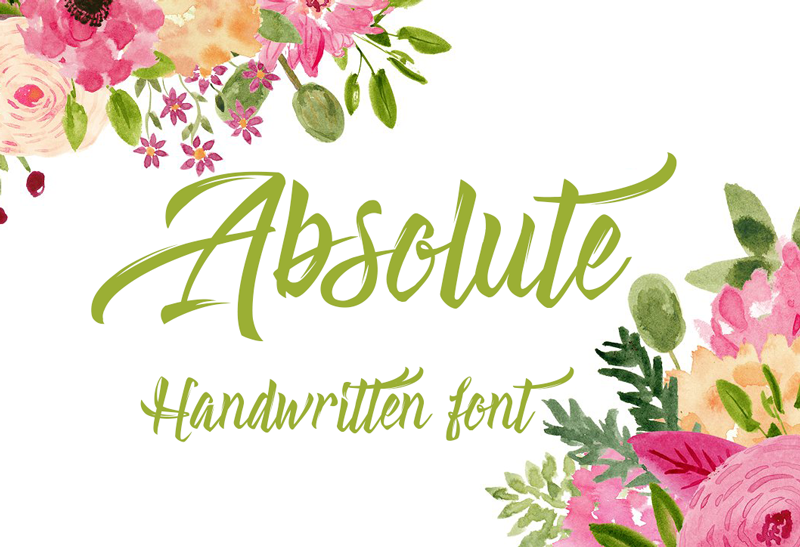
Absolute Font – Download Grátis
A fonte Absolute Font é uma escolha perfeita para aqueles que procuram um script elegante e fluido. Ela foi criada pelo designer Octotype e oferece um acabamento cuidadosamente elaborado, ideal tanto para projetos pessoais quanto comerciais. Os detalhes delicados da letra, sua facilidade de leitura e seu equilíbrio entre força e flexibilidade tornam-a uma fonte versátil que se adequa a uma variedade de aplicações. Se você é um designer gráfico buscando adicionar um toque único aos seus projetos, Absolute Font provavelmente será o item que sua coleção ainda está faltando. Ela pode ser baixada gratuitamente para uso pessoal ou comprada com um licenciamento comercial para usos mais ampliados. Para obter mais informações ou realizar seu pedido, visite .